50 восхитительных дизайнерских шрифтов бесплатно
Хотя существует широкий спектр шрифтов, доступных для загрузки в Интернете, дизайнеры продолжают отслеживать новинки, и использовать их в своей работе. Будь то веб-сайт, брошюра или другая реклама. Тем не менее, бесплатные шрифты не всегда могли похвастаться хорошим качеством. Обычно красивые шрифты – это платные шрифты. Однако, теперь можно найти подходящий вам шрифт, и абсолютно бесплатно его скачать. Сегодня всем доступны ясные, красивые и эффективные шрифты. Многие великие дизайнеры теперь предлагают профессиональные шрифты высокого качества скачать которые вы можете совершенно бесплатно.
Предлагаю вашему вниманию отличную коллекцию из 50 стильных шрифтов, которые вы можете мгновенно загрузить и использовать, что будет мощным толчком для вашего дизайна. Эти шрифты абсолютно бесплатны для личного использования, а если применять их правильно, то они сделают очень красивой практически любую работу в области печати или веб-дизайна. Идите вперед и не забудьте сделать правильный выбор шрифта! Кстати вот тут можно посмотреть
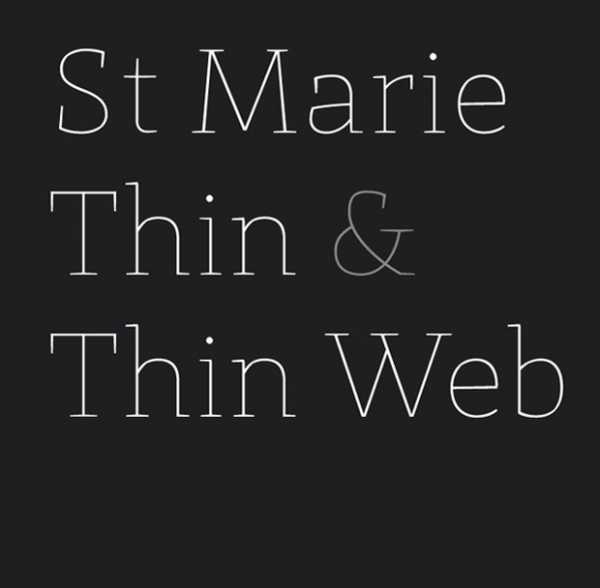
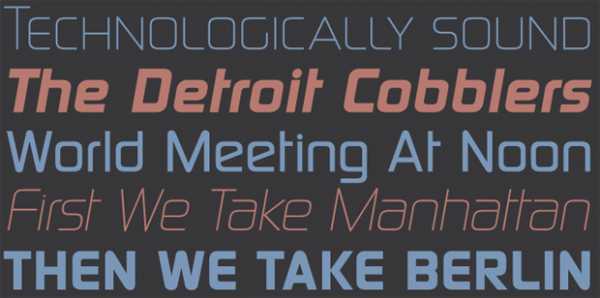
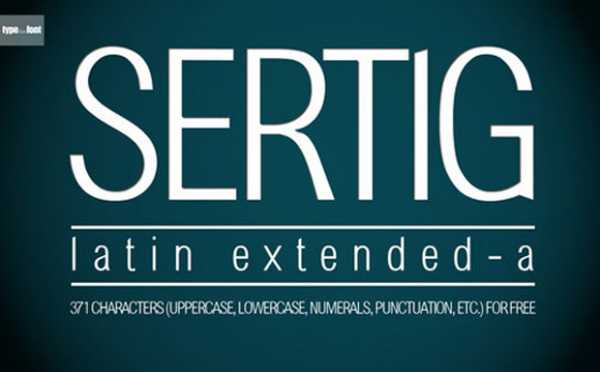
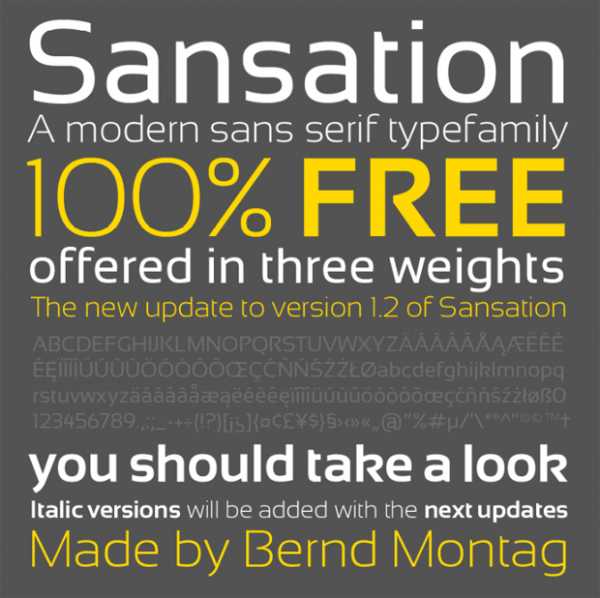
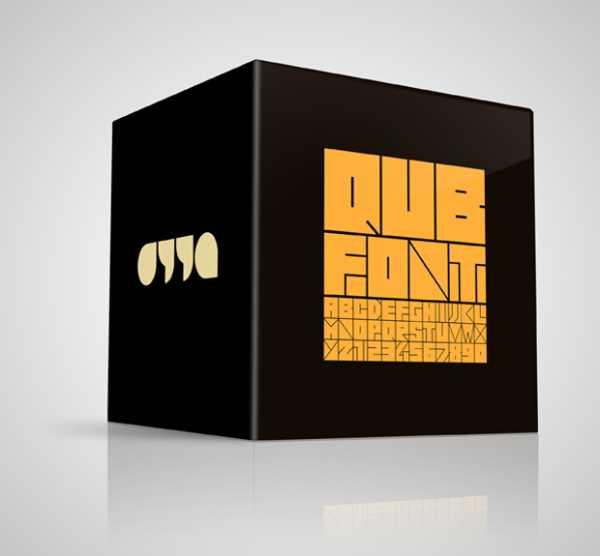
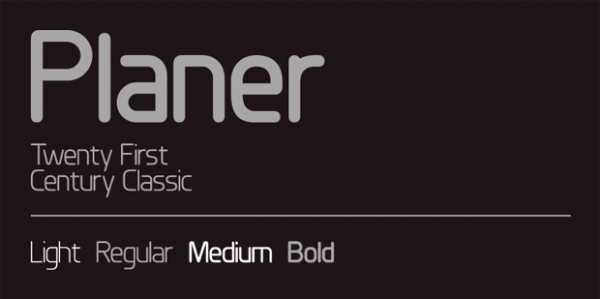
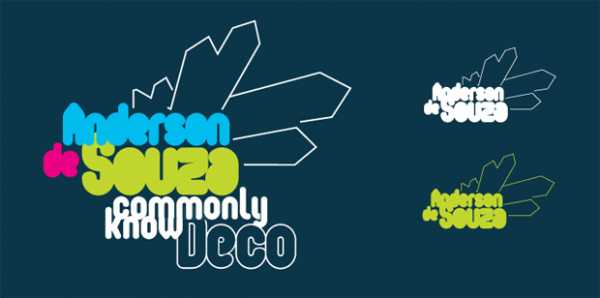
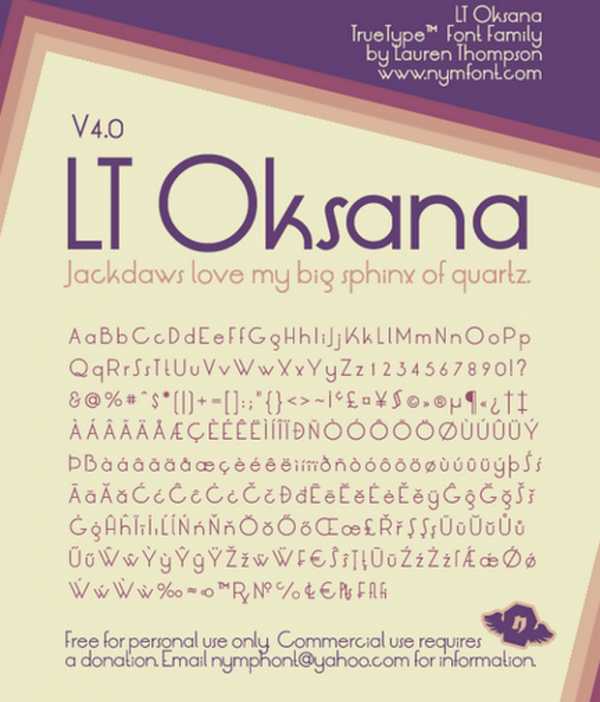
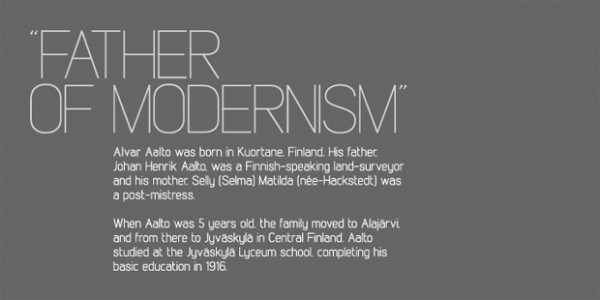
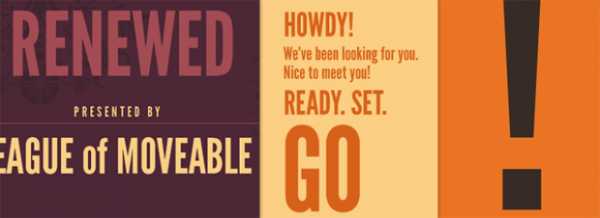
27. Шрифт Gabriel Serif
28. Округлый печатный шрифт Gabriel Serif V. 2
29. Печатный шрифт FR Hopper (430 & 431) (Требуется регистрация)
30. Шрифт Dilys
31. Шрифт в кантри стиле Jacobine (Требуется регистрация)
32. Шрифт Skyhook Mono (Требуется регистрация)
33. Красивый аккуратны шрифт My Fair Cody
34. Шрифт db Outline (Требуется регистрация)
35. Шрифт db Kopix (Требуется регистрация)
36. Потертый шрифт Leander